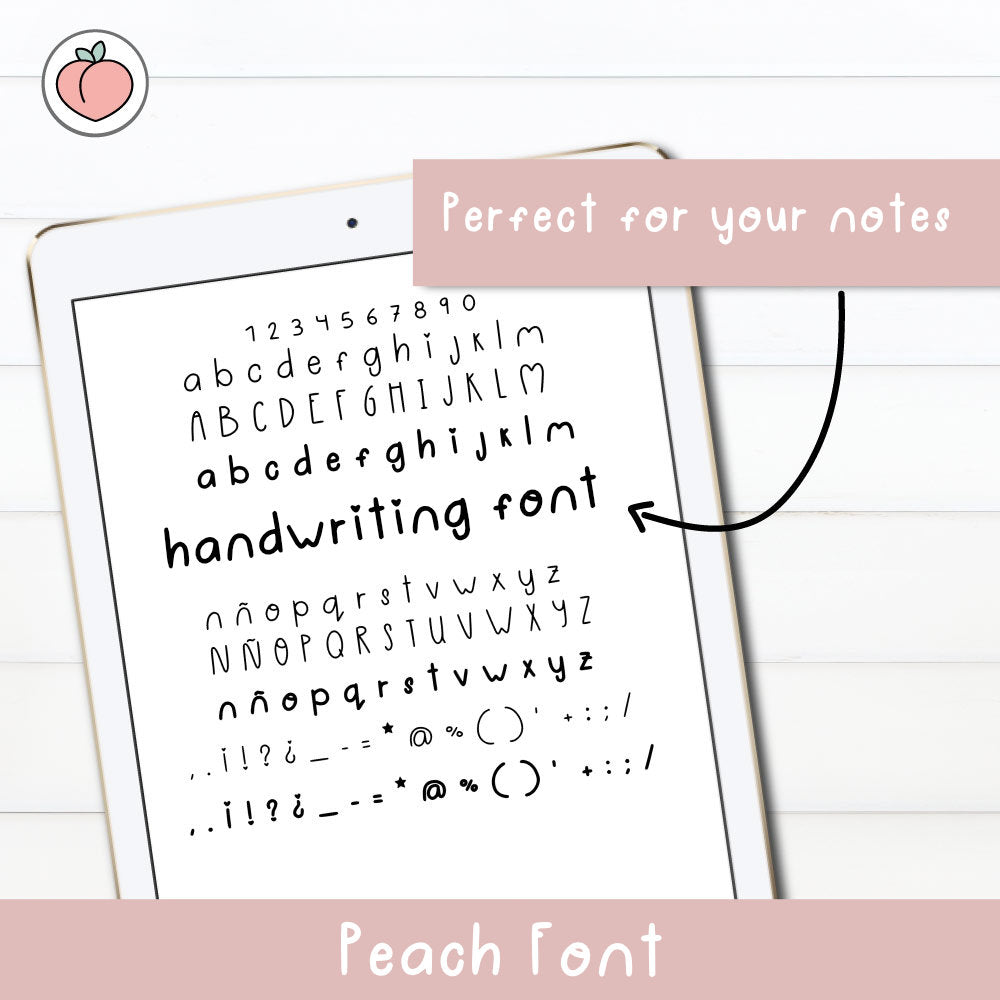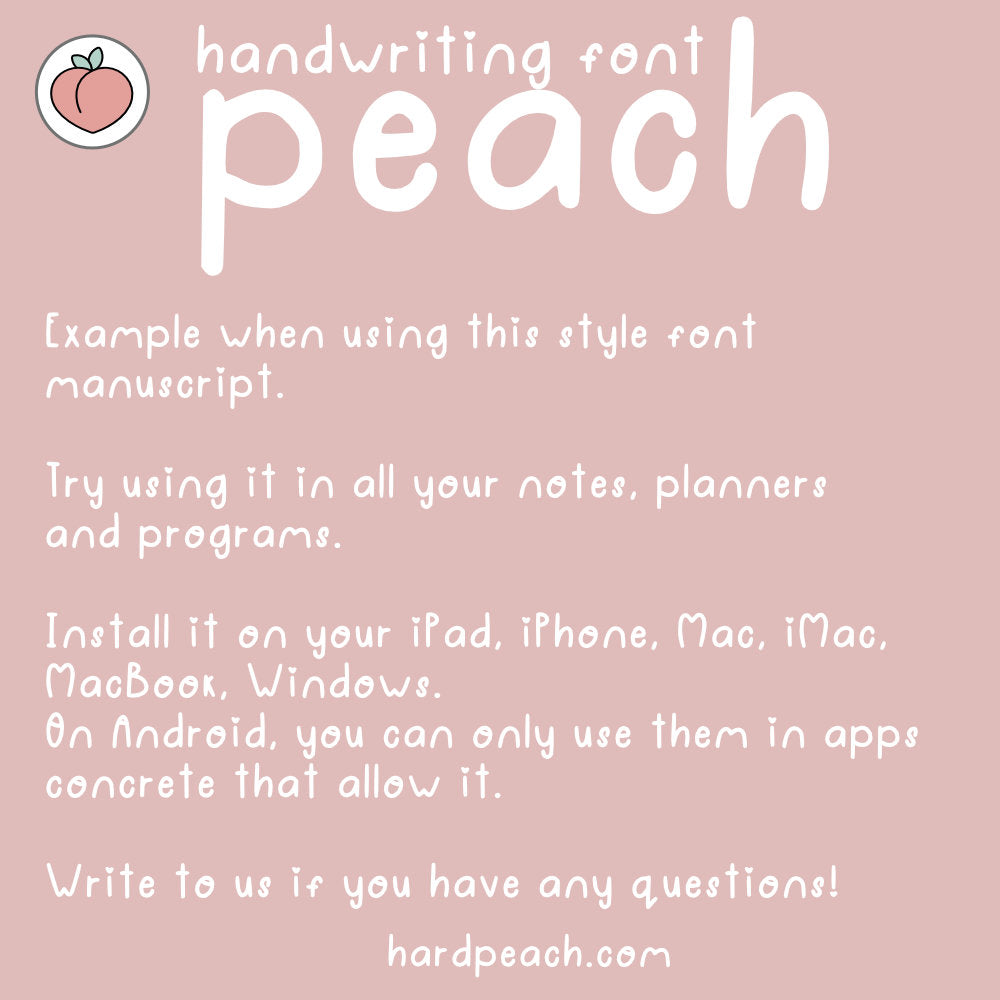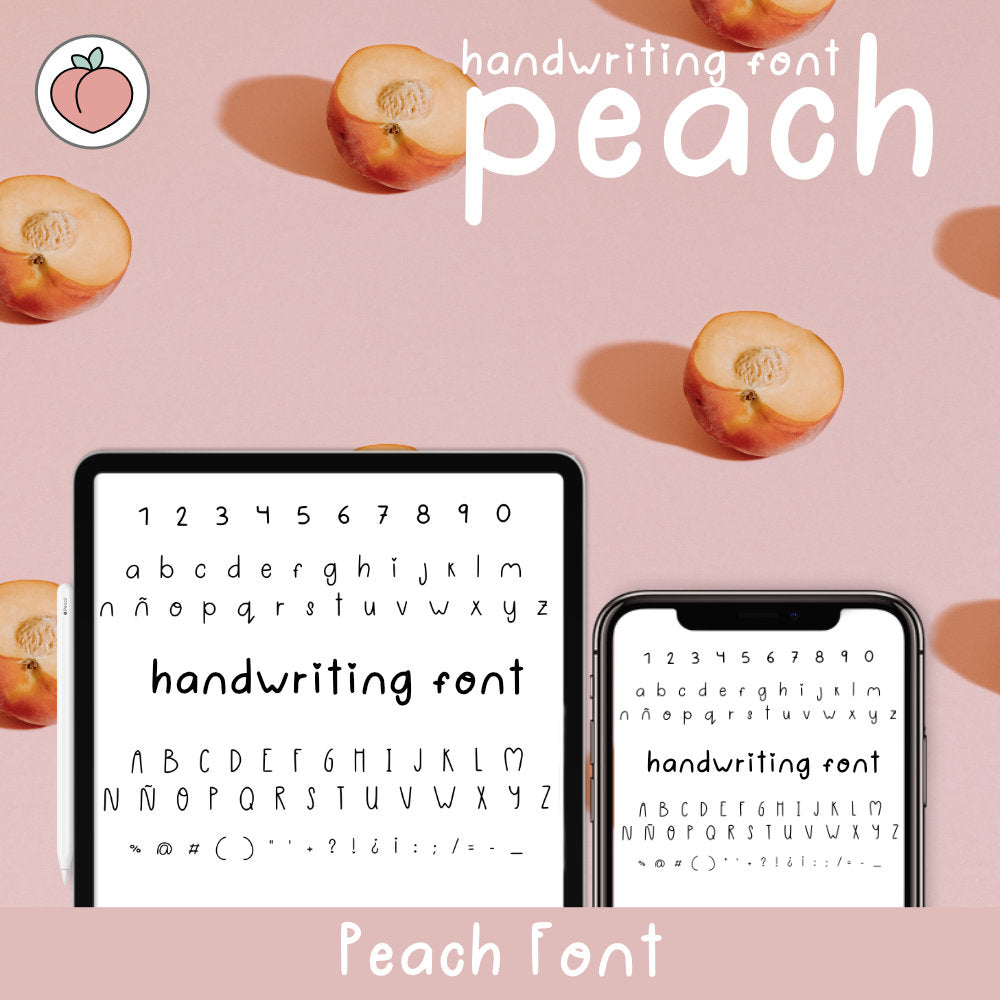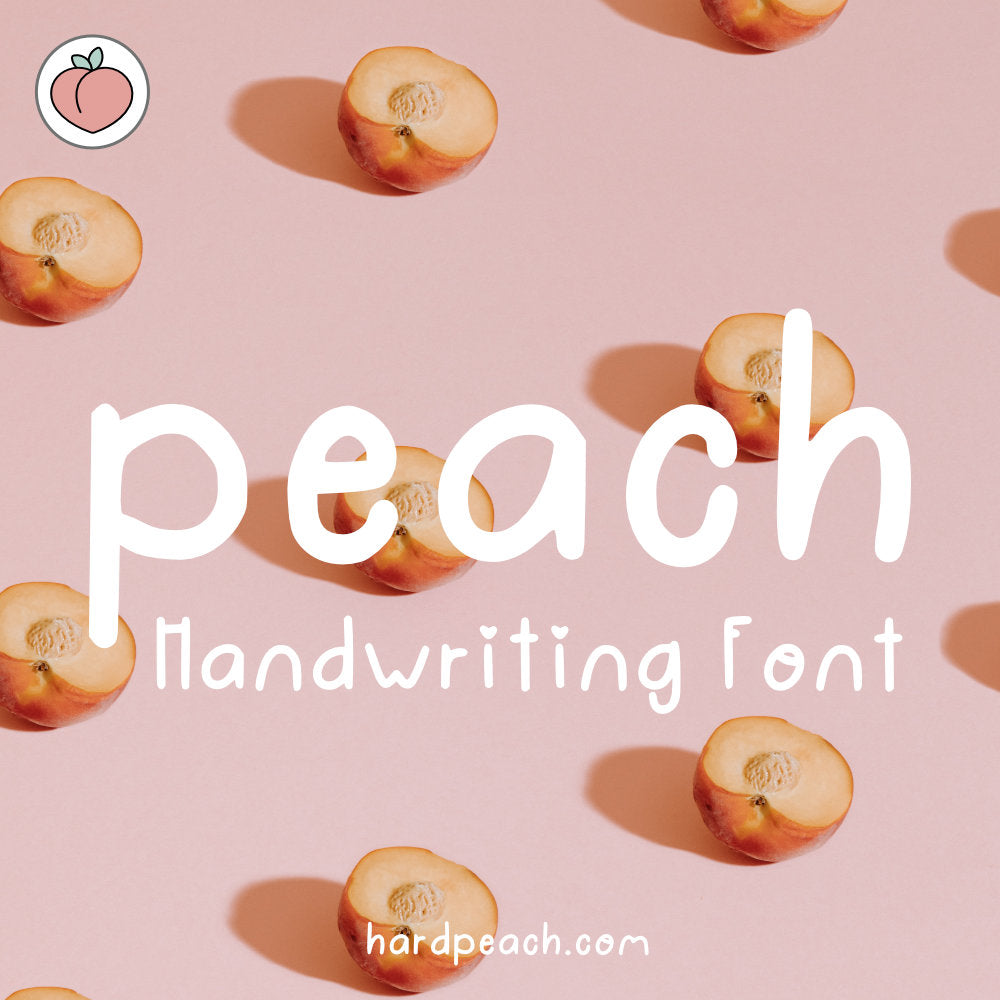
PEACH HANDWRITTEN FONT
Esta fuente es perfecta para notas en inglés y español, ya que incluye todos los caracteres esenciales:
• Letras mayúsculas y minúsculas
• Números
• Vocales con acentos (español)
• Acentos abiertos (à)
• Caracteres especiales, incluyendo las letras ñ y ç
¡Eleva tu experiencia de toma de notas con esta hermosa fuente manuscrita que añade un toque personal a todo tu contenido escrito!